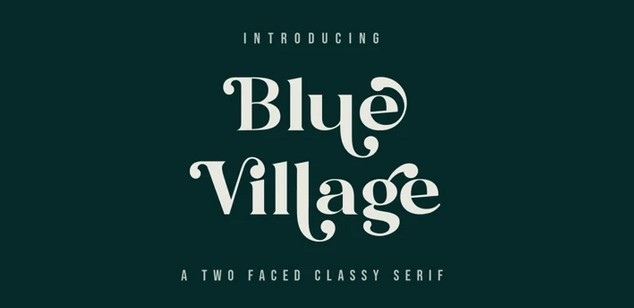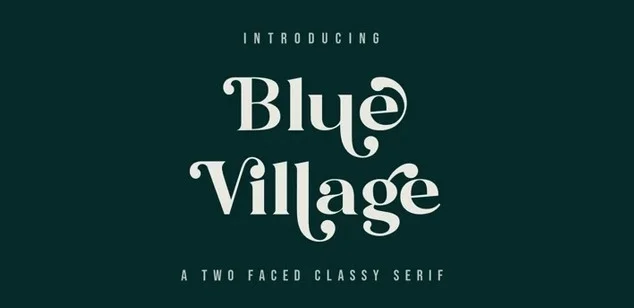
[Myfonts] Blue Village Font (2021)
Название: Blue Village Font (2021)
Blue Village
- двуликий современный или винтажный шрифт Serif с причудливым, игривым, уникальным и универсальным винтажным стилем.
Он прекрасно смотрится на мониторах и легко читается в текстовом формате.
Этот шрифт также имеет множество уникальных чередований и лигатур, которые позволят создать удивительные дизайнерские проекты.
Blue Village с его винтажным / ретро стилем хорошо подходит для брендинговых проектов, логотипов, свадебных дизайнов, постов в социальных сетях, рекламы, упаковки продуктов, дизайна товаров, этикеток, фотографий, водяных знаков, приглашений или любых других проектов, над которыми вы работаете.